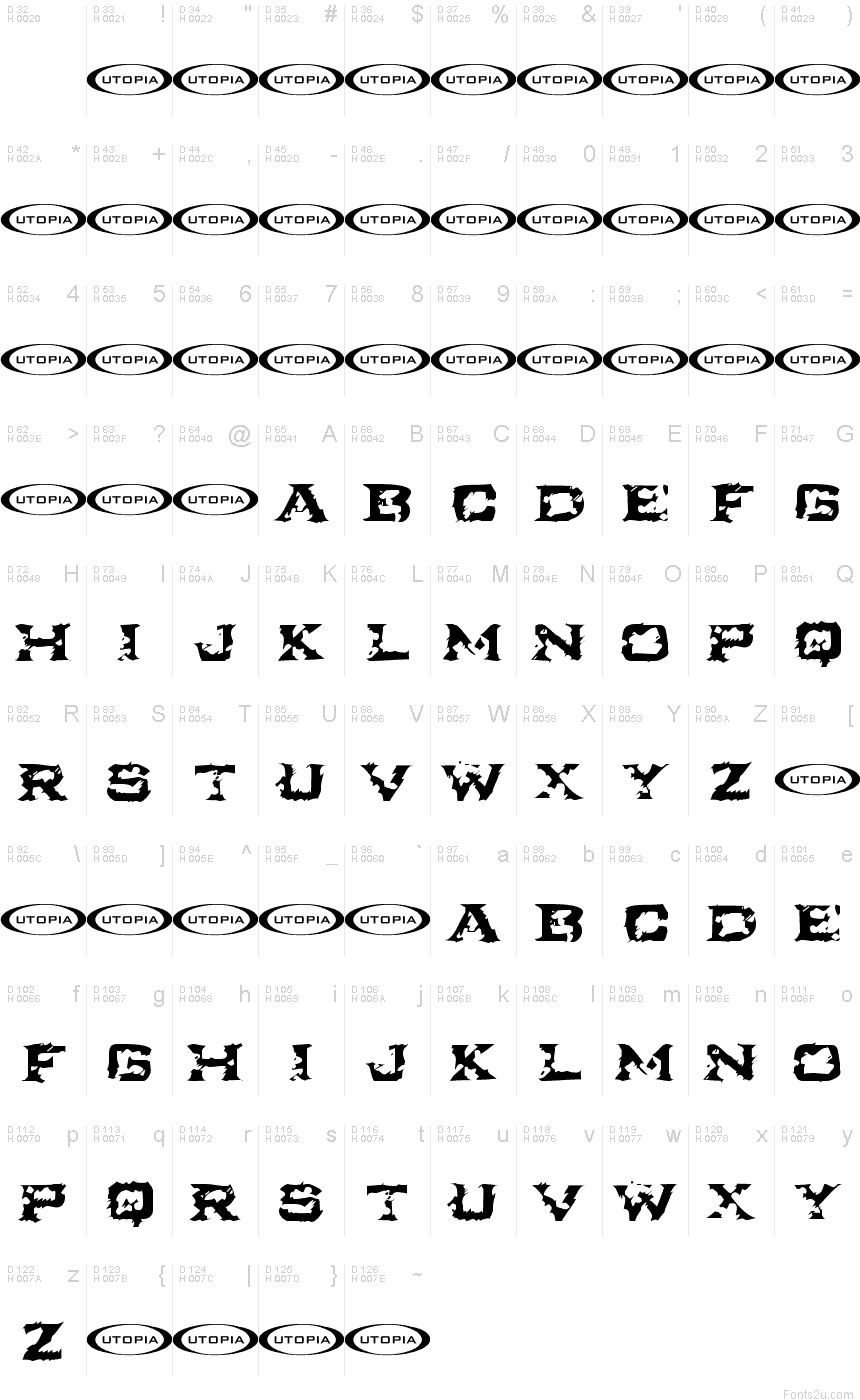
Ikarus Turbulence od Utopiafonts to darmowy, zniekształcony krój pisma typu display, który wygląda, jakby został poszarpany przez wiatr i ogień. Każda litera to czarna, poszarpana sylwetka z postrzępionymi krawędziami, ostrymi wypustkami i białymi prześwitami, które przypominają pęknięcia w starym kamieniu lub podarty papier. Gęsta, atramentowa tekstura natychmiast przyciąga wzrok, dzięki czemu nawet pojedyncze słowo staje się logo lub gotową grafiką.
Ten darmowy font świetnie sprawdza się na plakatach horrorów, logotypach zespołów metalowych, ulotkach na Halloween, zinach undergroundowych, tytułach gier i mrocznych okładkach albumów. Użycie Ikarus Turbulence w dużym rozmiarze pozwala w pełni wyeksponować te drobne, pęknięte detale, dodając Twojemu projektowi surowej, niebezpiecznej energii. W tekście głównym połącz go z prostym, geometrycznym bezszeryfem, aby zachować czytelność, pozwalając jednocześnie zniekształconym literom przejąć główną rolę.